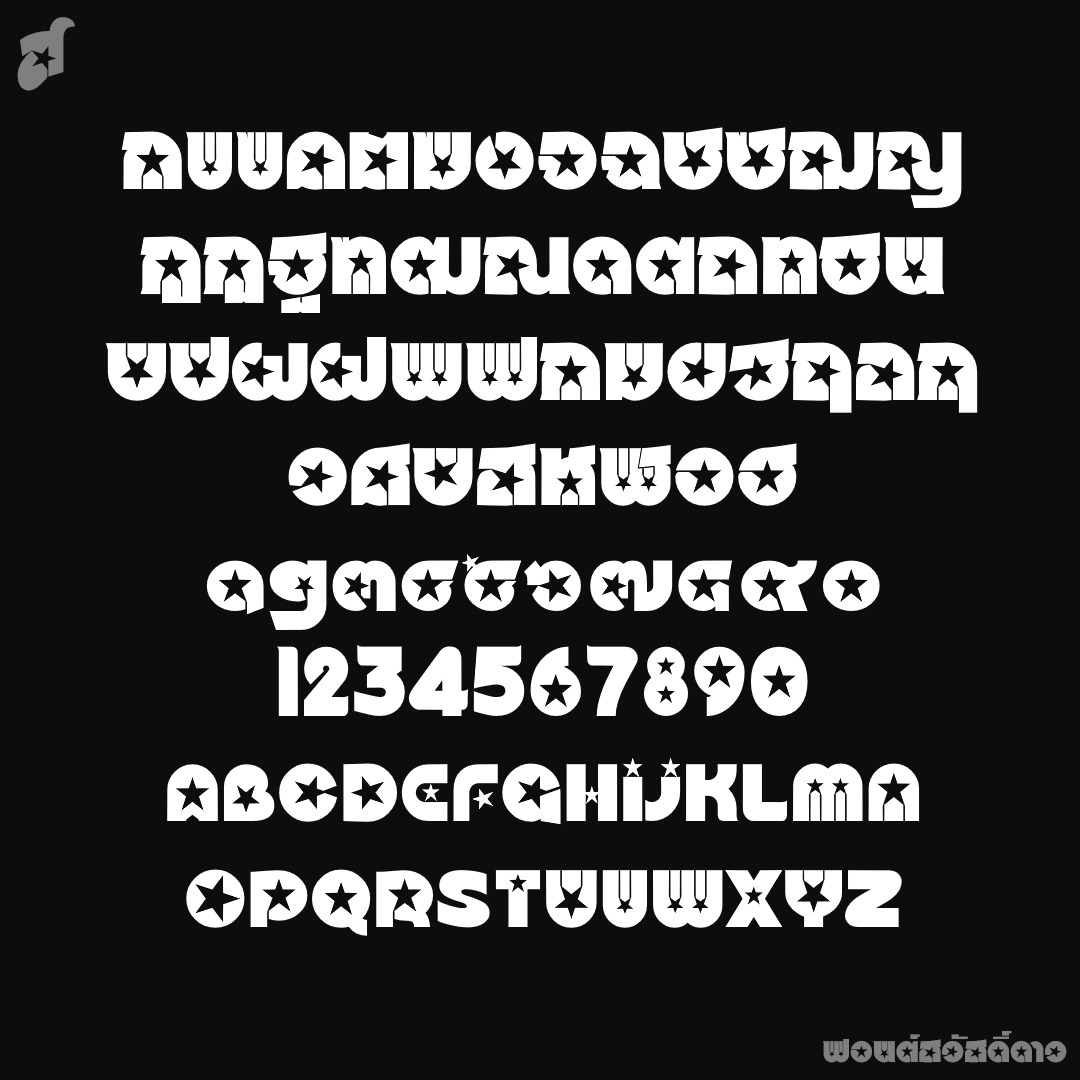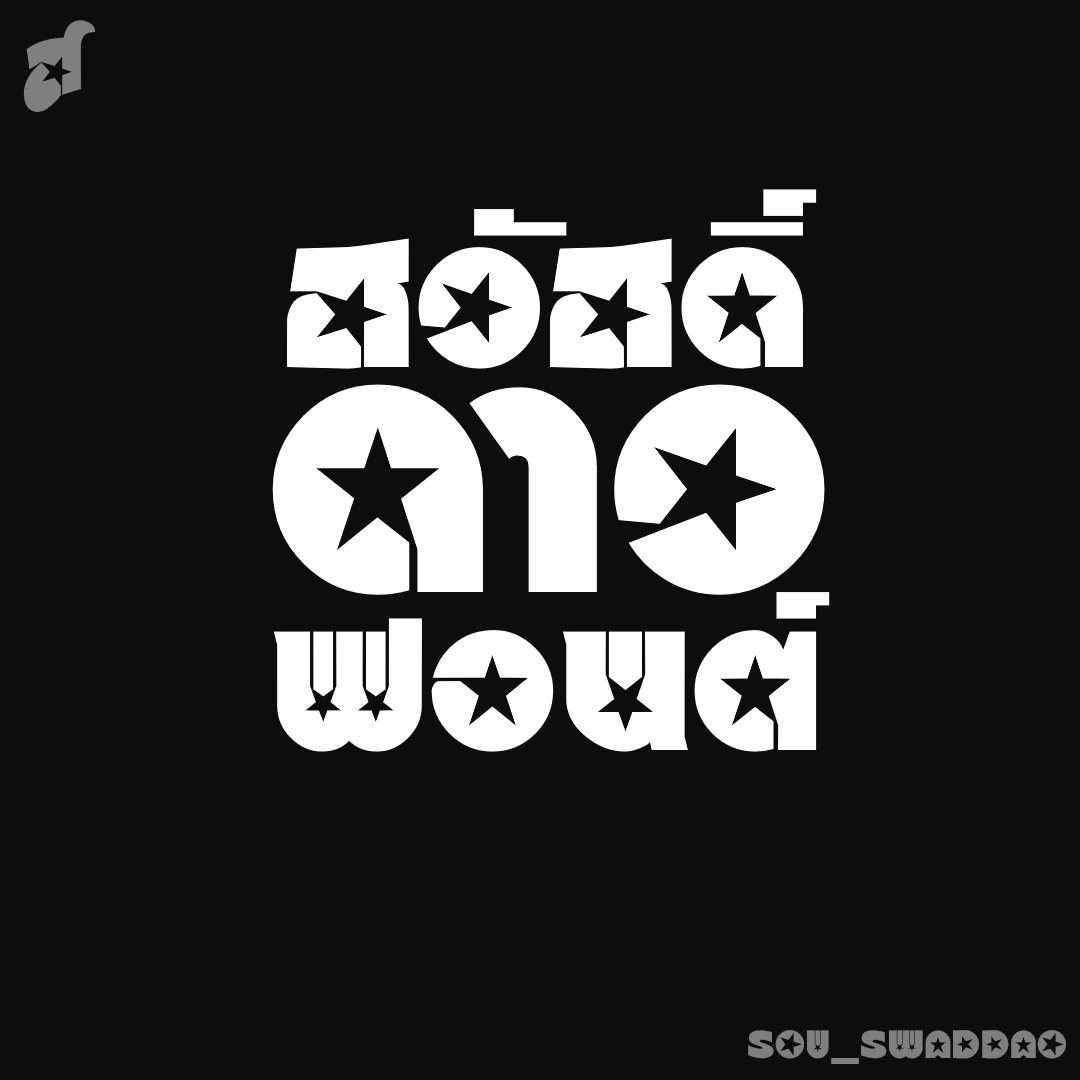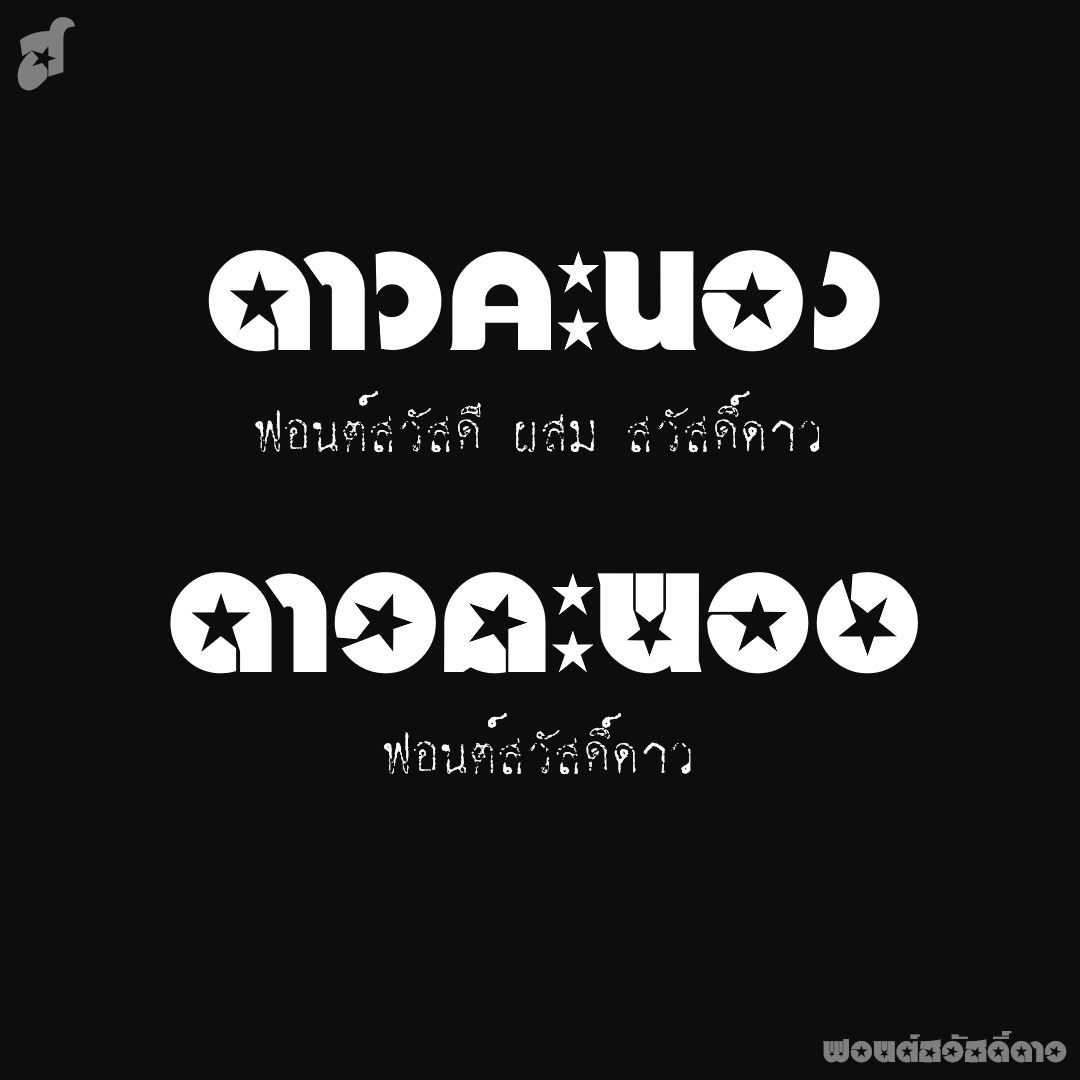
ฟอนต์ สวัสดิ์ดาว
ฟอนต์สวัสดิ์ดาว ต้นทางจาก หนังเรื่อง เทพธิดาท่าเรือ(cinderella liberty 1973) เป็นฟอนต์ตกแต่ง ..ถ้ารู้สึกว่าเยอะไป ให้ใช้ผสมกับฟอนต์สวัสดี
ชื่อฟอนต์ : สวัสดิ์ดาว
ฟอนต์สวัสดิ์ดาว ต้นทางจาก หนังเรื่อง เทพธิดาท่าเรือ(cinderella liberty 1973) เป็นฟอนต์ตกแต่ง ..ถ้ารู้สึกว่าเยอะไป ให้ใช้ผสมกับฟอนต์สวัสดี